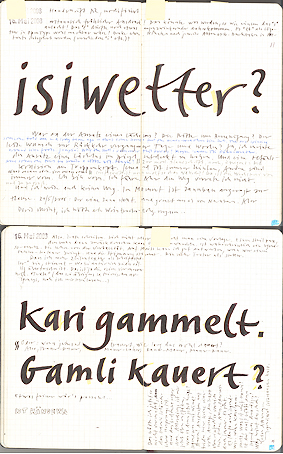
Weiblich, ca. Ende dreißig, ...
... resolut und mit beiden Beinen im Leben stehend. Nicht verspielt, sondern ausgeglichen und mit einem Gewissen Ausdruck. So stelle ich mir die Handschrift-Schrift vor, die ich für einen Auftrag brauche. Kann mich jemand verkuppeln?
@ Schwalbenkönig: okay, ich hab nur Bluemlein eingegeben, aber der brauch den Charles wohl auch noch. Vom Leuschke war eine passable dabei: https://www.myfonts.com/fonts/typesetit/oooh-baby/
Aber immer noch nicht 100% was ich gesucht hab. ICh brauch eine: "Ich-empfehle-Ihnen-das-Direktmarketing-Handschrift"
@ RM: Leider alles zu Ami-Style oder zu verpielt.
Und warum, mein lieber Kurvenschnellfliegerkönig, rätst du Alpha nicht zu dieser da?
Naja, weil sie ein wenig nach sensibel, Verunsicherung, nicht ganz selbstbewusst aussieht. Aber vielleicht interpretiere ich da auch zu viel Kafka hinein.
Naja, weil sie ein wenig nach sensibel, Verunsicherung, nicht ganz selbstbewusst aussieht.
Aha! Das leuchtet mir ein. — Dachte halt bloß, dass Alpha was direktmarketingelndes bräuchte und stellte mir vor, dass man da ja auch mit diesen Durchstreichungen diesbezüglich vielleicht herrlich herumspielen … na ja …
ICh brauch eine: "Ich-empfehle-Ihnen-das-Direktmarketing-Handschrift"
Dachte halt bloß, dass Alpha was direktmarketingelndes bräuchte und stellte mir vor, dass man da ja auch mit diesen Durchstreichungen diesbezüglich vielleicht herrlich herumspielen … na ja …
Na eh, hast ja eh recht. Und mit der Herr K. kann man vortrefflich spielen, so wie es aussieht. Ich mag es, wenn alle recht haben. :D
Nee, Jungens, lasst den Kafka in seinem Grab. Hier ist nichts angesagt, was zu amerikanisch, werblich oder altbacken aussieht. Einfach eine Handschrift einer zuverlässigen Sekretärin ohne heimliche Leidenschaften. Aber hier waren ja schon ein paar nette dabei. Ich brauche das für einen Slogan, also nicht mit rumgespiele, sondern clean und lesbar.
… ich doch nochmals … Slogan … also ein paar Worte bloß? Na dann … eigene Handschrift hast du ja … nimm den ganz fetten Leuchtstift … etwas rumkorrigieren mit schwarzem Kugelschreiber/Filzstift … reinzeichnen … jahrelange Kundenbindung garantiert ; )
Yo, viel zu krackelig, die Senkrechten solten recht niedrig und parallel sein, die untern Schwünge, wie beim "u" dynamisch und rund. Meine eigene Handschrift ist eine absolute Sauklaue! Ich kann zwar mit den Pinsel schreiben, aber das sieht dann zu amerikanisch aus, oder zu gewollt. Aber ich hab glaub, ich schon was.
Die Caflisch schaut ganz okay aus.